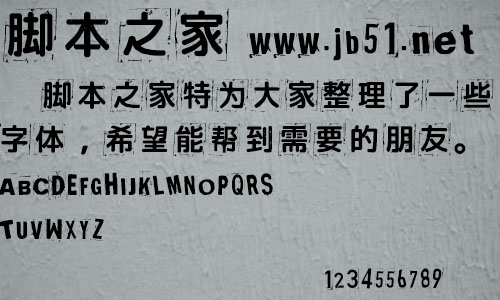
字體管家廢墟體是一款不錯(cuò)的藝術(shù)字體,由Aa字庫(kù)出品,字體筆觸粗實(shí),字形端正,具有很好的視覺(jué)感,適合應(yīng)用于藝術(shù)設(shè)計(jì)、平面宣傳設(shè)計(jì)、網(wǎng)頁(yè)設(shè)計(jì),書(shū)法字帖等領(lǐng)域,需要的朋友可以前來(lái)本站下載。